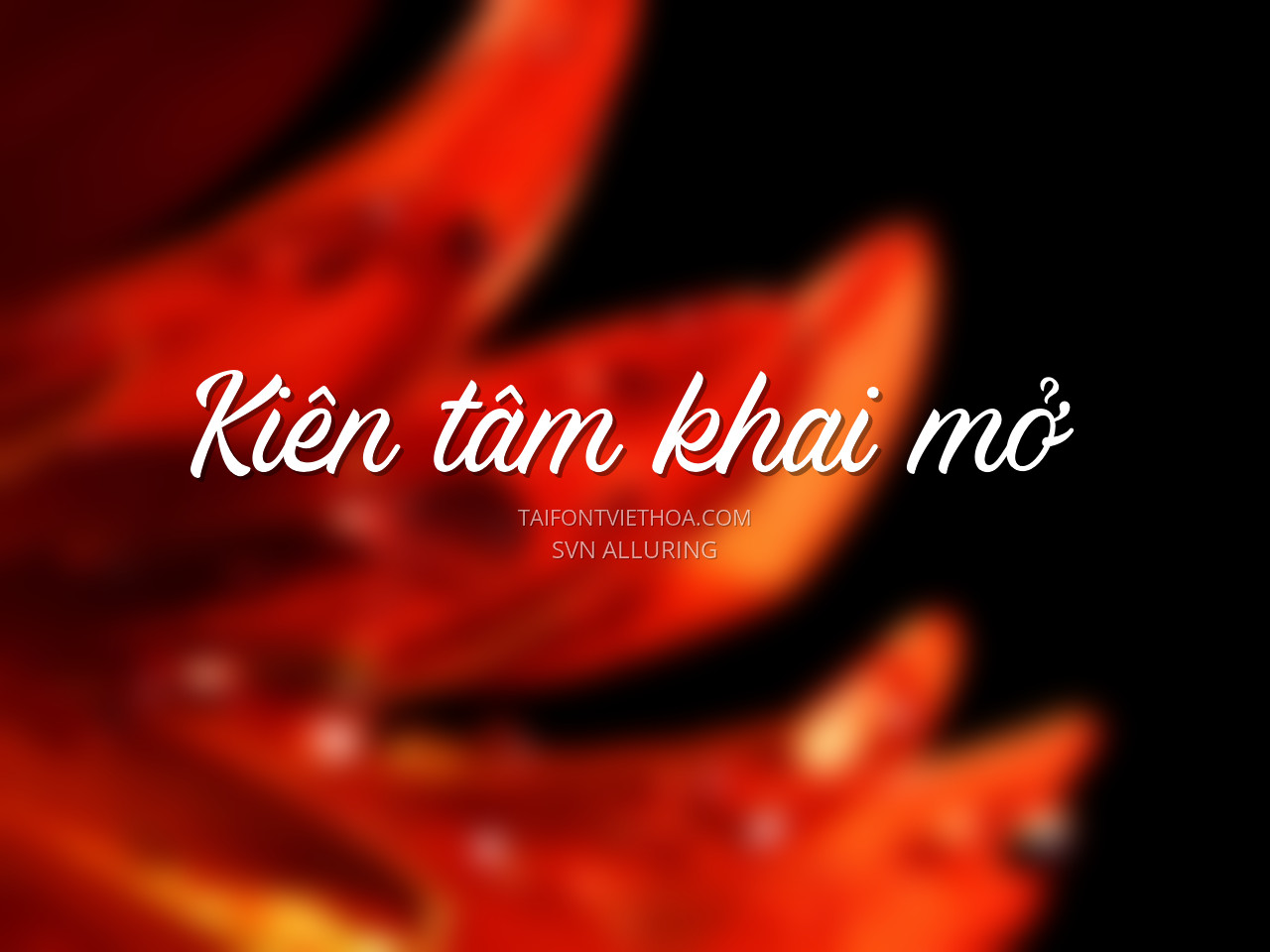
Font việt hóa SVN Alluring
Giới thiệu về font SVN Alluring – Kiểu chữ script mềm mại, thanh lịch và duyên dáng
SVN Alluring là phiên bản Việt hóa của font Alluring – một kiểu chữ script mang phong cách mềm mại, thanh lịch và rất duyên dáng. Font được thiết kế với các nét chữ uyển chuyển, nhẹ nhàng và tinh tế, tạo cảm giác gần gũi và nữ tính, rất phù hợp cho các dự án thiết kế thiệp cưới, thiệp mời, bao bì mỹ phẩm và các sản phẩm sáng tạo cá nhân.
Phiên bản Việt hóa của SVN Alluring đã được Taifontviethoa.comchăm sóc kỹ lưỡng, hỗ trợ đầy đủ dấu tiếng Việt cùng hơn 60 ngôn ngữ khác. Font giữ nguyên nét mềm mại, uyển chuyển và tự nhiên của bản gốc, giúp các nhà thiết kế dễ dàng áp dụng trong nhiều dự án sáng tạo với phong cách nhẹ nhàng, thanh lịch và duyên dáng.
Thiết kế viết tay uyển chuyển – Lý tưởng cho thiệp cưới và thương hiệu mỹ phẩm
SVN Alluring sở hữu các nét chữ mềm mại, liền mạch với độ nghiêng nhẹ nhàng và các ligature tinh tế, tạo nên sự hài hòa và bay bổng trong tổng thể thiết kế. Font mang lại cảm giác nữ tính, duyên dáng và rất phù hợp cho tiêu đề, logo, bao bì hoặc các phần thiết kế cần điểm nhấn mềm mại và thanh lịch.
Ứng dụng lý tưởng: thiệp cưới, thiệp mời, logo thương hiệu mỹ phẩm, bao bì sản phẩm cao cấp, bìa sách nghệ thuật, poster sự kiện và các dự án sáng tạo cần phong cách nhẹ nhàng, duyên dáng. Ngành nghề phù hợp: cưới hỏi, mỹ phẩm, thời trang, nghệ thuật, truyền thông sáng tạo và các thương hiệu định vị theo phong cách nữ tính, thanh lịch.